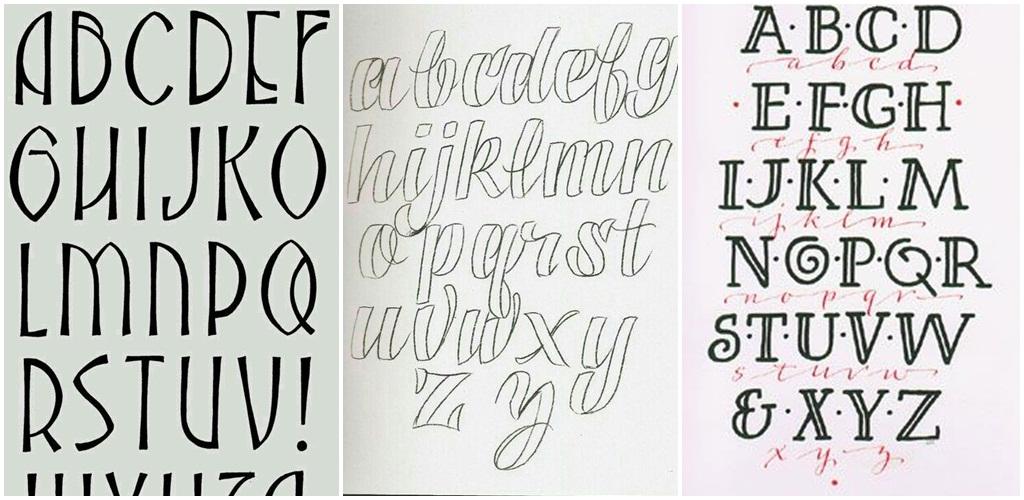
30+ Бесплатных рукописных шрифтов | by Writes
С новыми трендами на типографику дизайнеры все больше и больше нуждаются в уникальных шрифтовых сочетаниях.
Шрифтов не бывает много, тем более рукописных. Именно поэтому мы сделали подборку крутых, рукописных шрифтов. Все шрифты бесплатны и готовы к использованию.
Кириллица там тоже есть!
33 лучших бесплатных шрифта за лето — Оди
Всё лето в сообществе «Новые шрифты» я почти ежедневно публиковал по новому шрифту.
Лето кончилось и пришло время составить подборку лучших и бесплатных.
Шрифты с кириллицей и латиницей
Бесплатный декоративный палочный шрифт с кириллицей Eleventh Square (otf, ttf)
Бесплатный рукописно-декоративный шрифт с кириллицей Charming (otf)
Бесплатный декоративный шрифт с кириллицей Reef
Бесплатный рукописный шрифт с кириллицей Bemount v.1.1 (otf)
Бесплатный декоративный шрифт с кириллицей Reef
Бесплатный рукописный шрифт с кириллицей Bemount v.1.1 (otf)
Бесплатный брусковый шрифт с кириллицей Ikra Slab
Гарнитура Intro Rust (кириллица)
Словолитня Фонтфабрик выпустила большую гарнитуру из 214 шрифтов.
Все поддерживают кириллицу. В гарнитуре 4 основных стиля: Intro Rust, Intro Script, Intro Head and Intro Goodies (символы). Три шрифта раздают бесплатно (приложены). Полная гарнитура сейчас продается за 49$, потом будет стоить 490$. Полная презентация по ссылке.
Бесплатный декоративный шрифт с кириллицей Shumi (otf)
Бесплатный набор литер с кириллицей Carrote (eps)
Шрифты только с латиницей
Бесплатный гротеск в 8 начертаниях Chivo (ttf, otf, woff, eot)
Бесплатный декоративный шрифт в четырех начертаниях Vibery (ttf)
Бесплатный декоративный шрифт в пяти начертаниях Viterous (ttf)
Бесплатный набор литер Julep (eps, ai)
Бесплатный декоративный шрифт Hidden Cinema (ttf)
Бесплатный геометрический гротеск Sen в трех начертаниях (otf + webfont)
Бесплатный декоративный шрифт Gothic AX Hand (Beta)
Бесплатный декоративный шрифт Helena (ai)
Бесплатный декоративный шрифт Middlecase в 8 начертаниях (otf)
Бесплатный гротеск Genome с открытыми исходниками (Open Source)
Бесплатный гротеск BSRU Bansomdej
Бесплатный декоративный шрифт Firefly 2015 (ttf+otf)
Бесплатный декоративный шрифт Amsdam (ttf)
Бесплатный декоративный шрифт Stoked (ttf)
Бесплатный декоративный шрифт Sea (ttf)
Бесплатный декоративный шрифт Polygonal (ttf)
Бесплатный декоративный шрифт Kohta (desktop)
Бесплатный декоративный шрифт в пяти начертаниях Break (ttf)